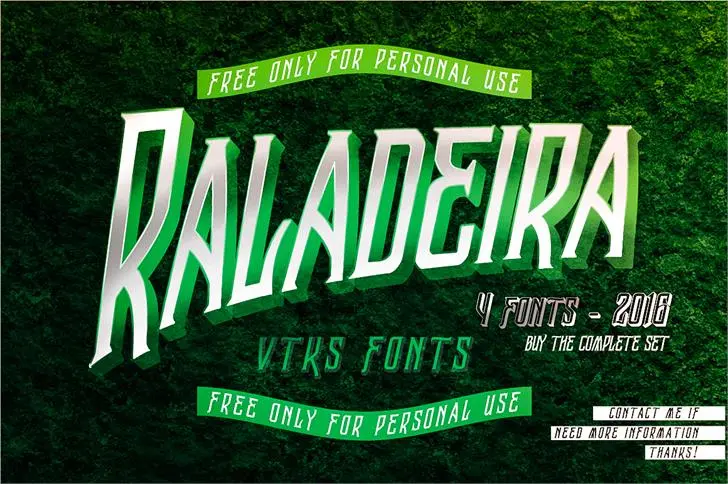
Vtks Raladeira 2 Font – Download Grátis
A Vtks Raladeira 2 é uma elegante fonte serif que traz sofisticação ao seu design visual. Inspirada no estilo de receitas de biscoitos, essa fonte oferece linhas suaves e detalhes cuidadosamente criados para tornar o texto atraente e profissional em qualquer aplicação comercial. A Hamilton é o designer por trás dessa criação única, cujos traços perfeitamente equilibrados enriquecem seu uso em materiais de impressão ou digital. Se você está procurando por uma fonte serif que pode destacar sua marca nas revistas, websites e materiais de marketing sem perder a sua identidade, a Vtks Raladeira 2 é uma opção ótima para se aventurar. Com seu design cuidadosamente projetado, ela traz um toque especial à sua criação. Visite o link fornecido para adquirir seu próprio autorização de uso da fonte em moeda estrangeira.